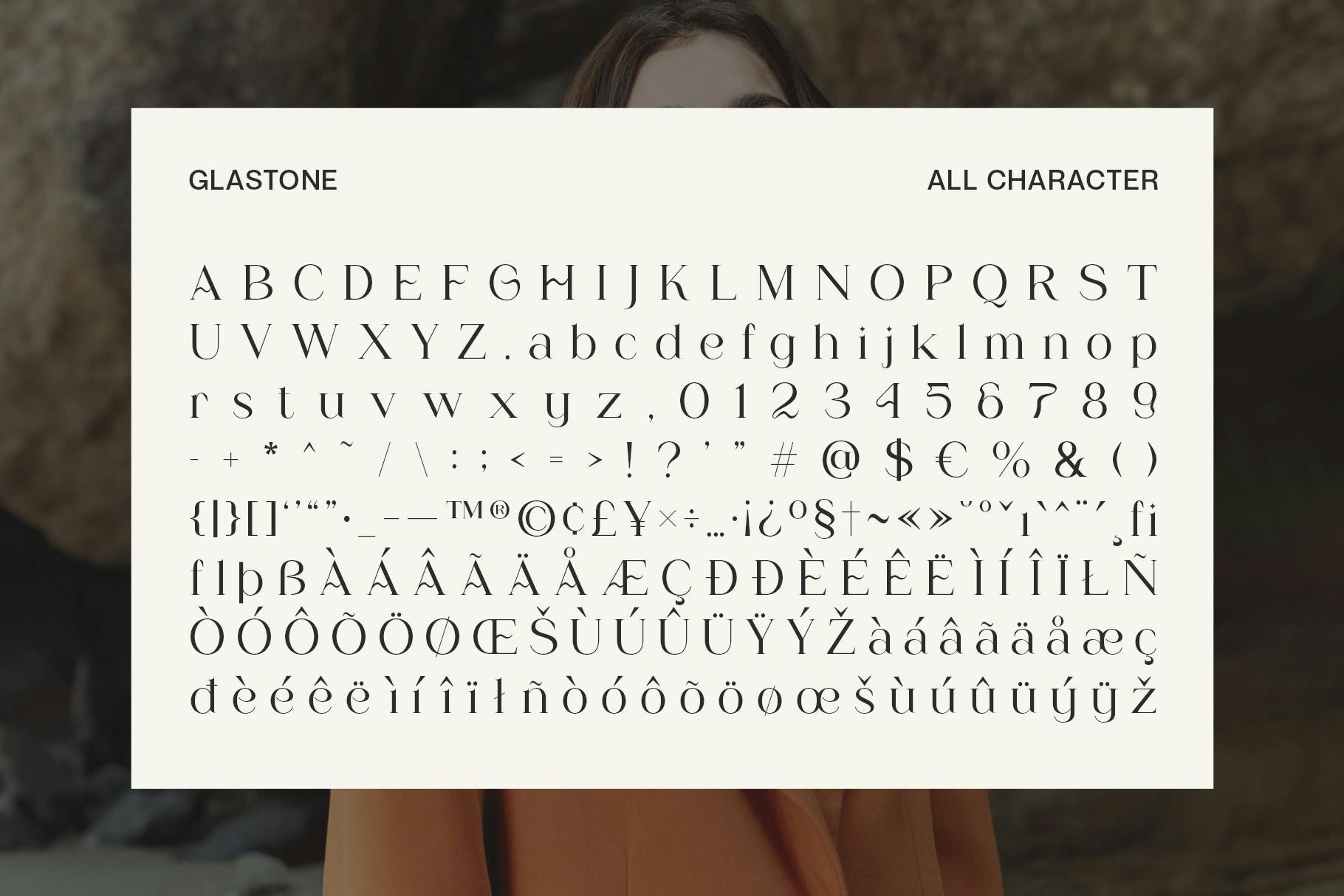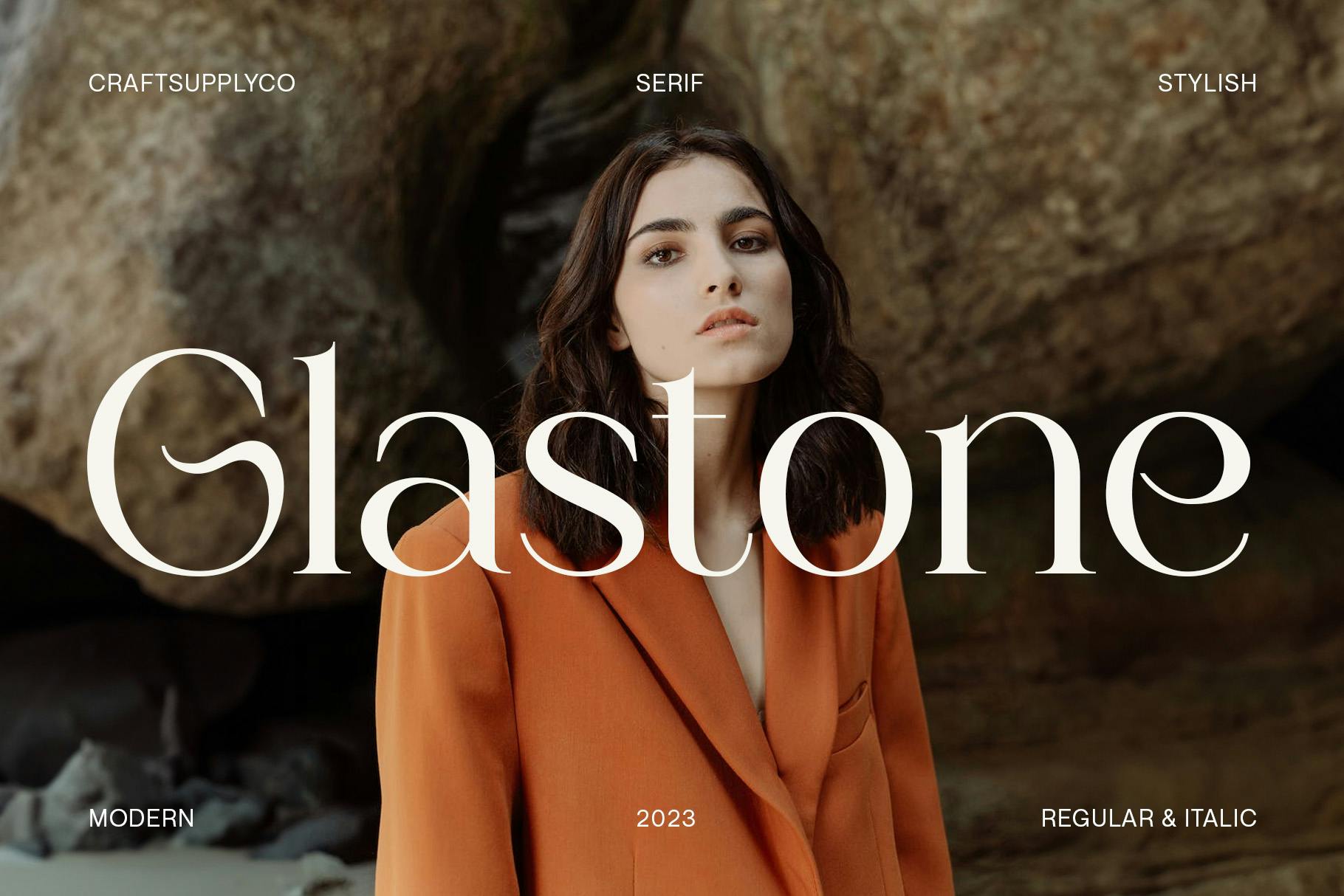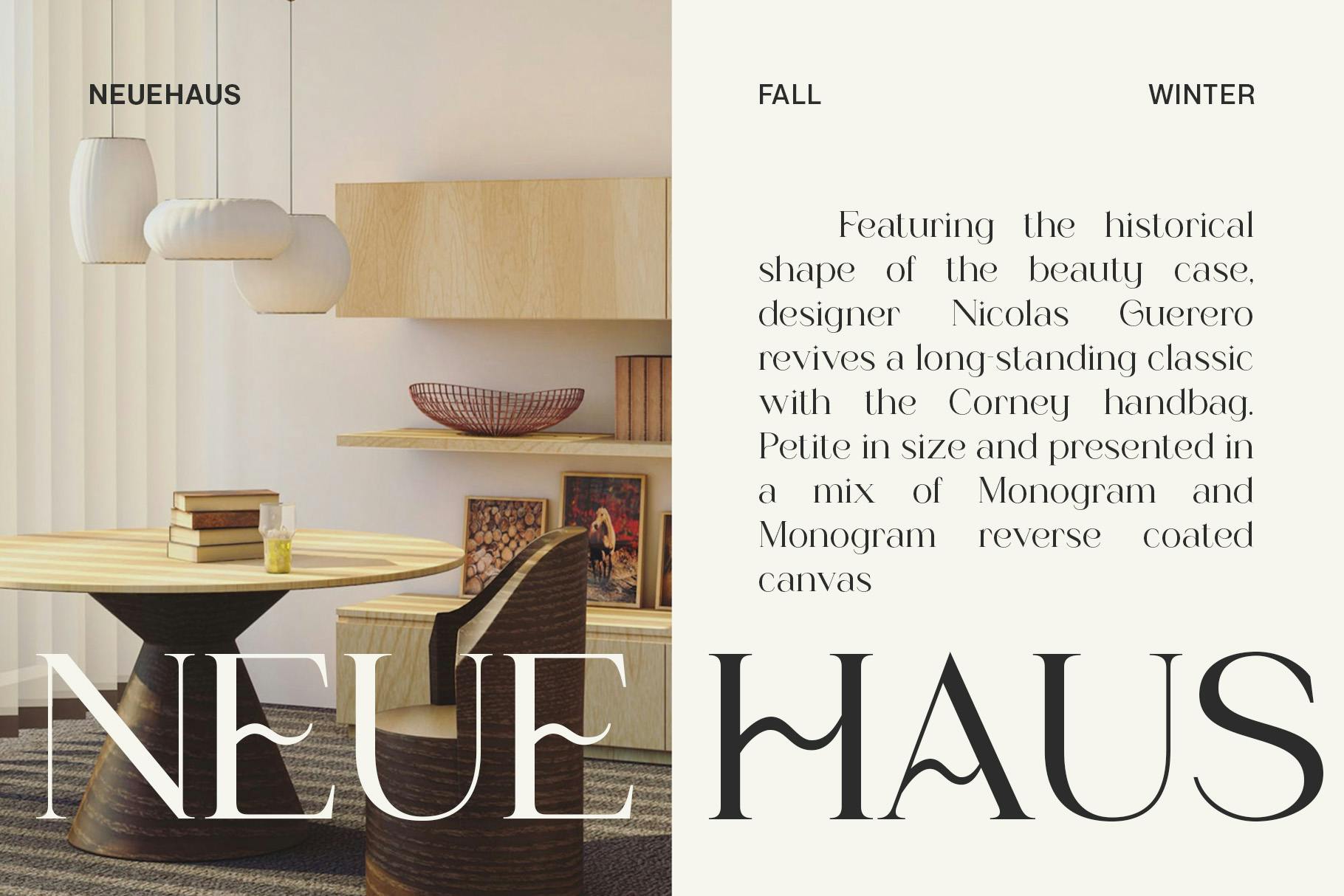
فونت گلاستون یک تایپفیس مدرن با طراحی سریف است که زیبایی و حس زنانه را بهطور بینقصی ترکیب میکند و حس کلاس و شیک بودن معاصر را القا مینماید. خطوط زیبا و زیباییشناسی مدرن این فونت، آن را به گزینهای ایدهآل برای پروژههایی تبدیل میکند که به دنبال تعادل بین ظرافت و مدرنیته هستند.
این فونت برای طراحی کارتهای تبریک، بستهبندی، هویت برند، پوستر و هر هدفی که میخواهد پروژه طراحی شما را جذاب و مدرن جلوه دهد، مناسب است. از کار با این تایپفیس لذت ببرید!